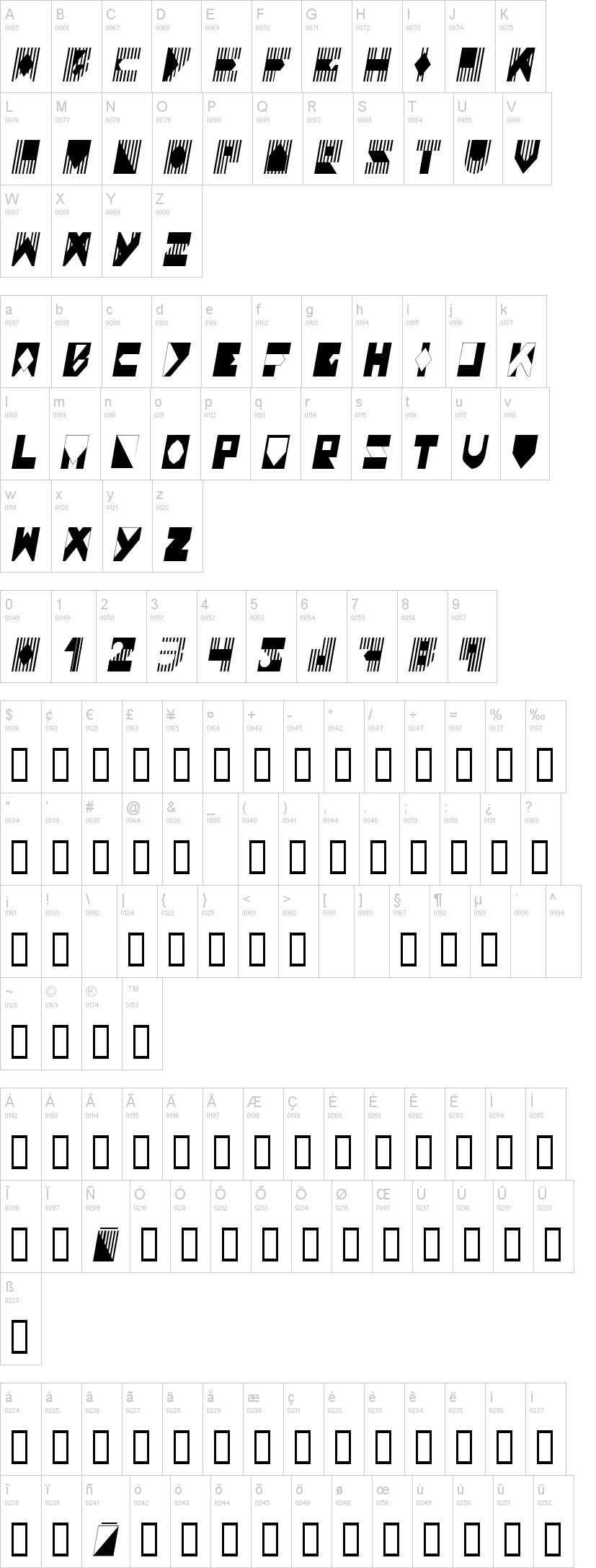
Note of the authorColonialistas es una tipografía realizada a base de banderas, como experimento para representar la invasión de una cultura en una zona. Pensado en que Uno de los primeros síntomas de sentirse invadido por otra cultura es su habla (la comunicación) y el identificador y representante mundial por excelencia de un país o zona son las banderas.